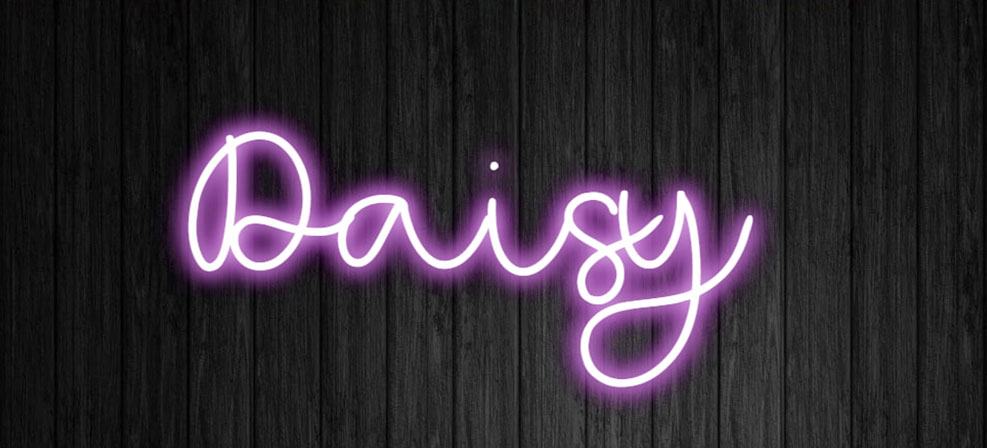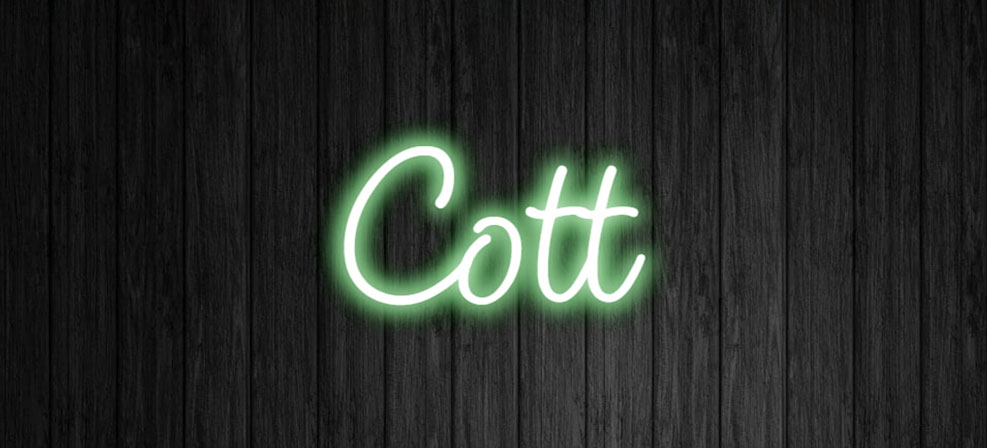
Font chữ LED Neon là nhóm các phông chữ được thiết kế mô phỏng lại ánh sáng phát ra từ những ống thủy tinh uốn cong của đèn neon sign, mang đậm phong cách sôi động của các thành phố không ngủ về đêm. Với cấu trúc nét chữ liền mạch, các đường cong mượt mà tối ưu cho việc uốn ống đèn và hiệu ứng phát sáng ảo diệu, nhóm phông chữ này là lựa chọn hoàn hảo cho các thiết kế biển hiệu quán bar, poster sự kiện âm nhạc, thời trang streetwear và bao bì sản phẩm cá tính. Doozypack.vn cung cấp link tải trọn bộ Font chữ đèn LED Neon chuẩn kỹ thuật, giúp bạn sở hữu phông chữ phát sáng độc đáo, hỗ trợ tiếng Việt mượt mà để hiện thực hóa mọi ý tưởng thiết kế phá cách.
Đặc điểm thẩm mỹ độc đáo của bộ font chữ LED Neon
Font chữ LED Neon không đơn thuần là một kiểu chữ viết tay; nó tái hiện trọn vẹn vật lý và ánh sáng của nghệ thuật trang trí ánh sáng đương đại.
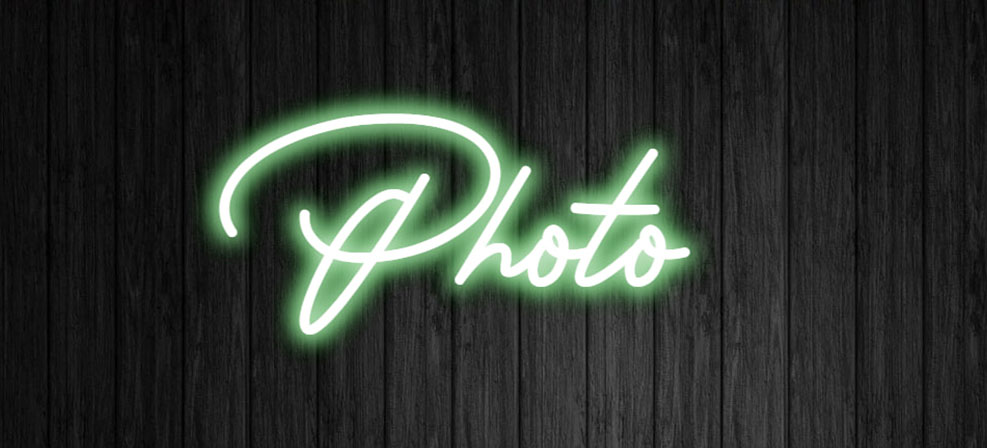
Phong cách ống thủy tinh phát sáng và nhịp điệu liên tục
Đặc trưng lớn nhất của Font chữ làm LED Neon là các con chữ được cấu thành từ một đường nét duy nhất (Monoline) hoặc các đoạn nối liền mạch không đứt đoạn. Thiết kế này mô phỏng chính xác cách thợ thủ công uốn ống thủy tinh để tạo hình chữ viết. Khi kết hợp cùng hiệu ứng phát sáng (Glow effect), phông chữ này mang lại sức nặng thị giác vượt trội trên nền tối, tạo cảm giác lung linh, huyền ảo và cực kỳ thu hút ánh nhìn.
Khả năng mô phỏng chân thực kỹ thuật uốn đèn Neon Sign
Các ký tự của Font chữ đèn LED Neon được tối ưu hóa để vừa phục vụ thiết kế đồ họa kỹ thuật số (làm bảng hiệu ảo, video), vừa hỗ trợ các đơn vị thi công uốn đèn thực tế bên ngoài đời thực. Hệ thống dấu thanh tiếng Việt được thiết kế tinh tế, kết nối liền mạch với thân chữ chính mà không làm gián đoạn dòng chảy ánh sáng của phông chữ.
Ưu điểm nổi bật của bản phông chữ đèn LED Neon Việt hóa
Khi ứng dụng các phông chữ hiệu ứng ánh sáng vào thị trường trong nước, sự chỉn chu về dấu câu là yếu tố quyết định đến tính chuyên nghiệp của ấn phẩm:
- Khắc phục triệt để lỗi dấu tiếng Việt: Phiên bản Việt hóa đã được đội ngũ thiết kế trau chuốt thủ công từng dấu câu. Các dấu sắc, huyền, hỏi, ngã, nặng được vẽ thanh mảnh, uốn lượn đồng điệu cùng thân chữ gốc, không gây cảm giác chắp vá hay đè nét làm mất hiệu ứng phát sáng.